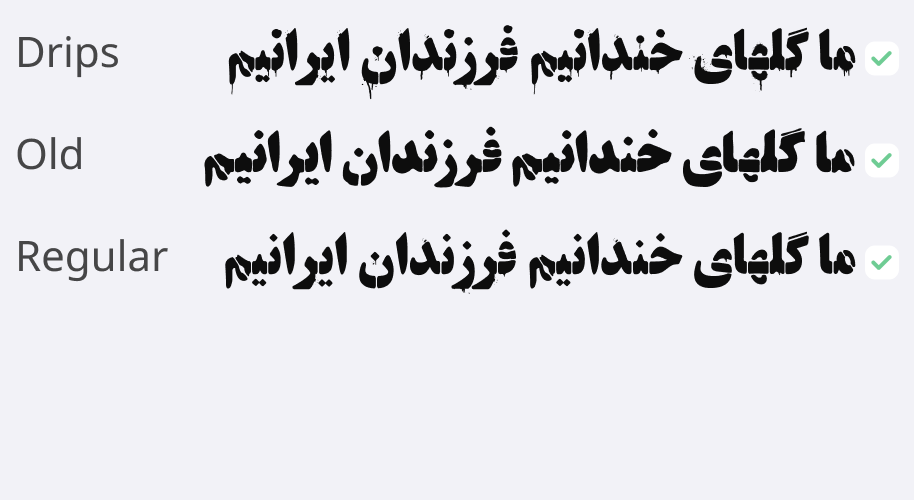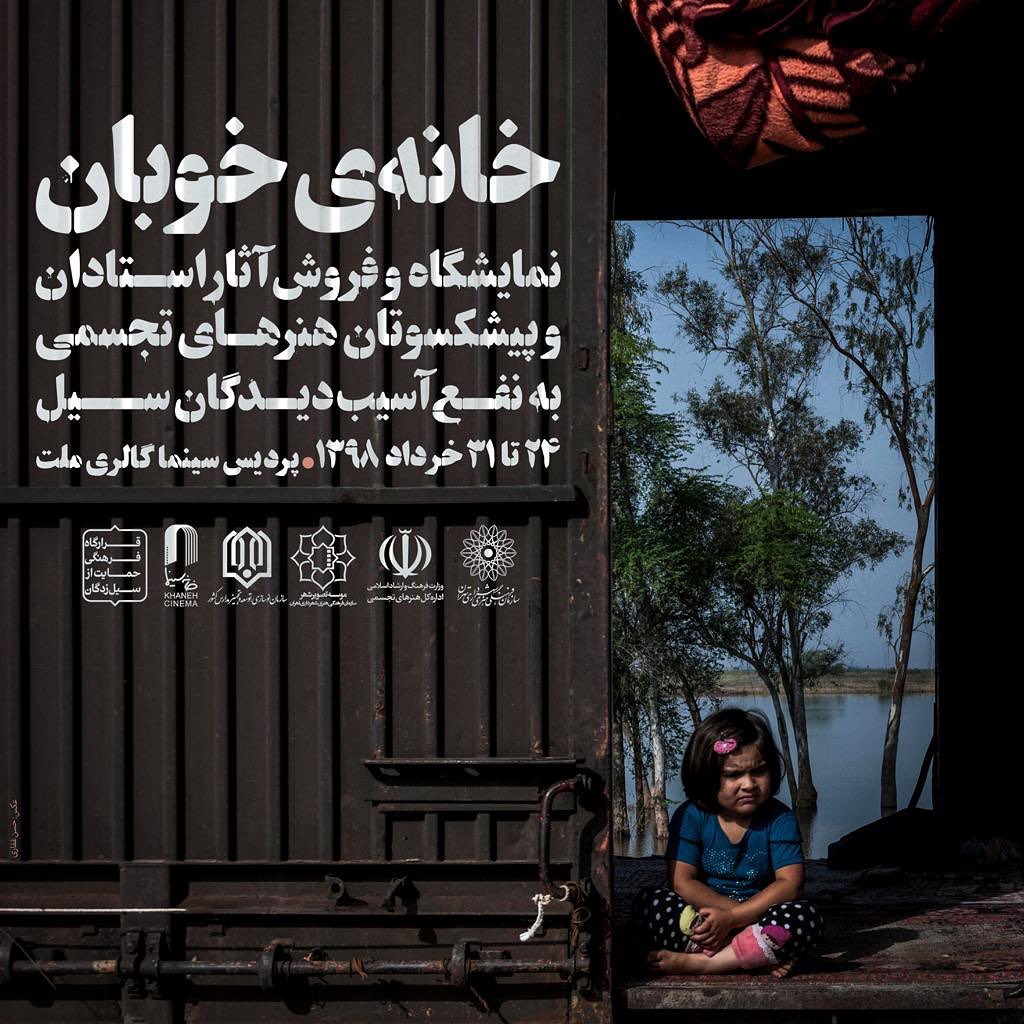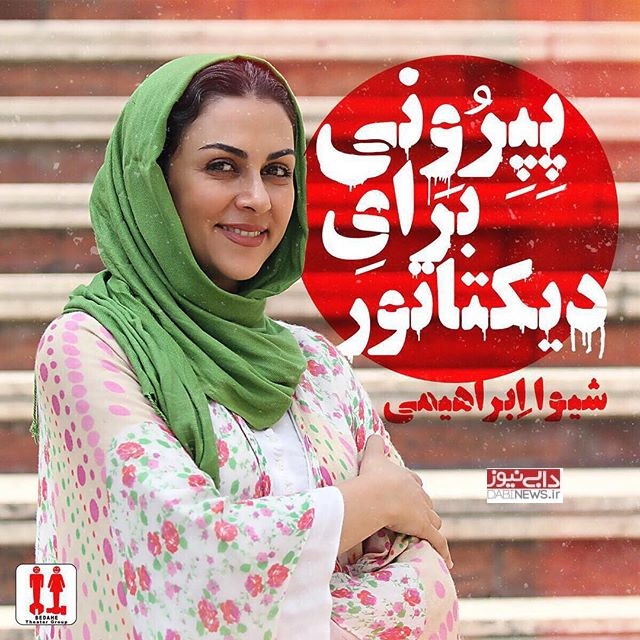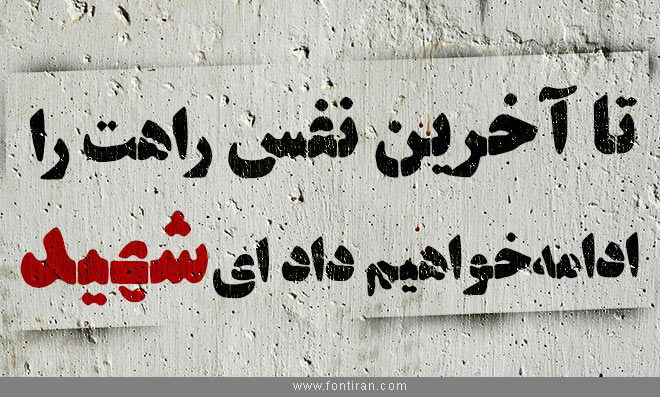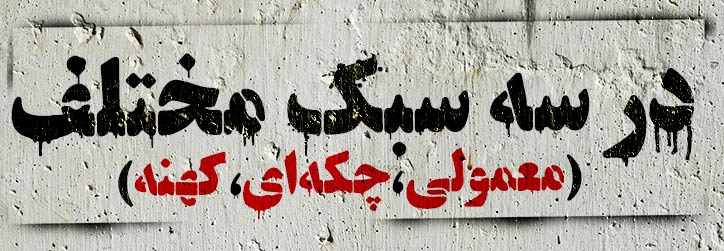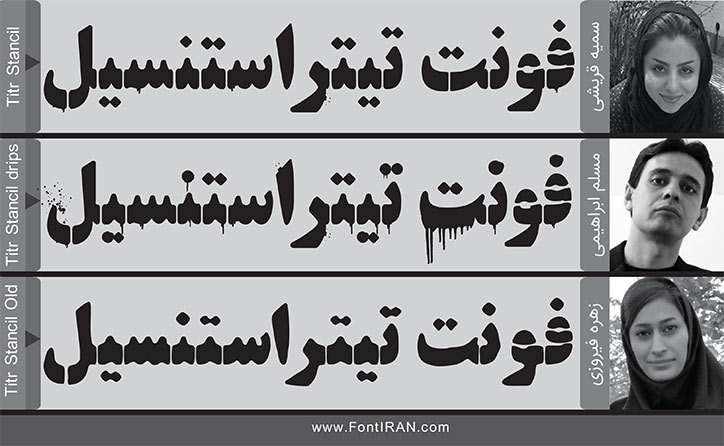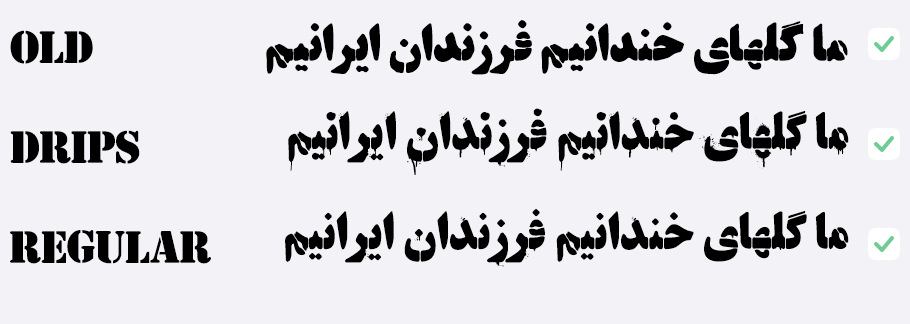
Titr Stencil : ساده ترین فونت این مجموعه است. این قلم در واقع همان تیتر است که پُل ها و انفصال های استنسیل به آن اضافه شده و مقدار نویز کمی در افکت آن وجود دارد.
Titr Stencil drips: در سبک drips یا همان چکه، نویز و افکت فراوان وجود دارد و تعداد زیادی از حروف افکت شرره کردن رنگ و اسپری را نشان می دهند.
Titr Stencil old: در فونت تیتر استنسیل کهنه با اینکه اصلا افکت شره اسپری و نویز وجود ندارد اما چون کاملا با دست استنسیل حروف بازسازی شده، حالت واقعی تری از شابلون های قدیمی را به نمایش میگذارد.
فونت تیتر گرافیتی استنسیل می تواند برای طراحی پوسترهای انقلابی و گرافیک برخی محصولات فرهنگی که حال و هوای انقلابی دارند، بسیار مناسب باشد.
مسلم ابراهیمی کارشناس ارشد گرافیک است که از سال ۱۳۸۸ بصورت پیگیر و حرفهای به طراحی تایپ فارسی مشغول بوده است. در سالهای ابتدایی دغدغه او تدریس طراحی تایپ در دانشگاه بود و پس از آن با راه اندازی وبسایت فونتایران تمرکز خود را به ساز و کار نشر و بازاریابی برای فونت فارسی تغییر داد. فونتهای طراحی شده توسط مسلم ابراهیمی طی سالهای ۱۳۹۳ تا ۱۳۹۶ توانست چهرهٔ تایپوگرافی وب و نرمافزار فارسی را تغییر دهد. مسلم ابراهیمی با راه اندازی وبسایت فونتایران توانست فرهنگ رعایت داوطلبانه کپی رایت فونت را در ایران رواج دهد و چالشهای فروش و کسب درآمد برای طراحان تایپ ایرانی را حل کند. :: فونت ایرانسنس از ساختههای مسلم ابراهیمی پر استفادهترین فونت وب و نرم افزار در ایران است. :: مسلم ابراهیمی در سال ۲۰۲۴ با فونت هستی توانست مقام دوم رقابت جهانی گرانشان را کسب کند.